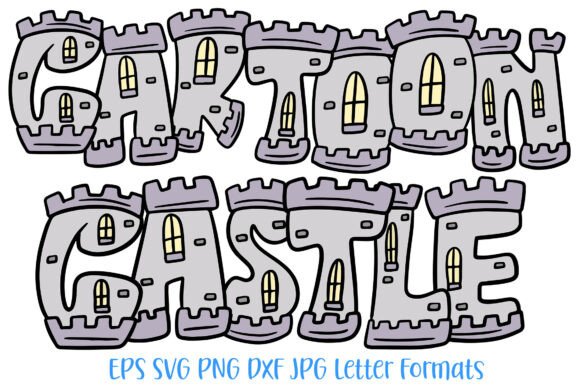
Cartoon Castle Font History Medieval ABC
Die richtigen Designelemente zu finden, kann eine Herausforderung sein, aber Cartoon Castle Font History Medieval ABC bietet eine außergewöhnliche Sammlung, die Ihre Arbeit sofort aufwertet.
Mit Präzision gefertigt, bietet Cartoon Castle Font History Medieval ABC saubere Vektoren, eine reibungslose Typografie und eine kommerzielle Lizenz für ein beruhigendes Gefühl.
Egal, ob Sie POD-Produkte (Print on Demand), Hochzeitseinladungen oder Social-Media-Grafiken erstellen, Cartoon Castle Font History Medieval ABC ist die ideale Wahl.
Zwar gibt es kostenlose Alternativen, doch fehlen ihnen oft die kommerziellen Rechte und die technische Perfektion von Cartoon Castle Font History Medieval ABC.